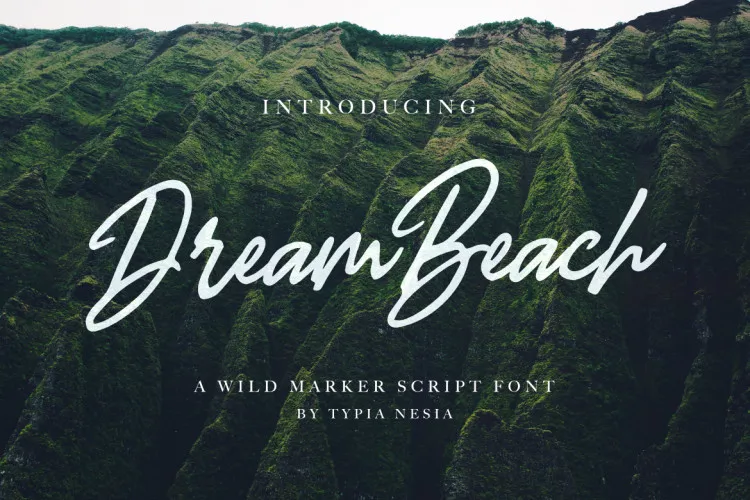
Dream Beach Script Font – Download Grátis
A Dream Beach Script Font é uma fonte de script que traz a essência de uma caligrafia esbranquiçada e descontraída, perfeita para quem busca um design criativo e único. Crie sua própria assinatura com esta opção elegante e divertida, ideal tanto para logomarcas quanto para designs em papelaria, como cartões e revistas. Além disso, é uma excelente escolha para aplicar em materiais de embalagem ou capas de livros, combinando perfeitamente com um estilo hipster moderno. Além dos usos citados anteriormente, esta fonte também se destaca na criação de adesivos e até mesmo como letras a mão no mercado do branding. Suavemente fluida e carregada de entusiasmo boêmio, ela traz uma vibe descontraída que complementará com perfeição qualquer design criado por meio de letra a caneta. Ideal tanto para aqueles que desejam algo diferente em seu projeto quanto para os amantes de designs únicos. A Dream Beach Script Font é um elemento indispensável para qualquer designer que procura uma fonte com personalidade e estilo, oferecendo-lhes uma gama versátil de possibilidades semelhante ao uso da caneta na praia. Seja em sua próxima criação, ou esteja buscando algo que faça suas ideias sair do papel mais rápido e prazerosamente, essa fonte certamente será um recurso valioso para qualquer designer em seu arsenal de recursos gráficos.